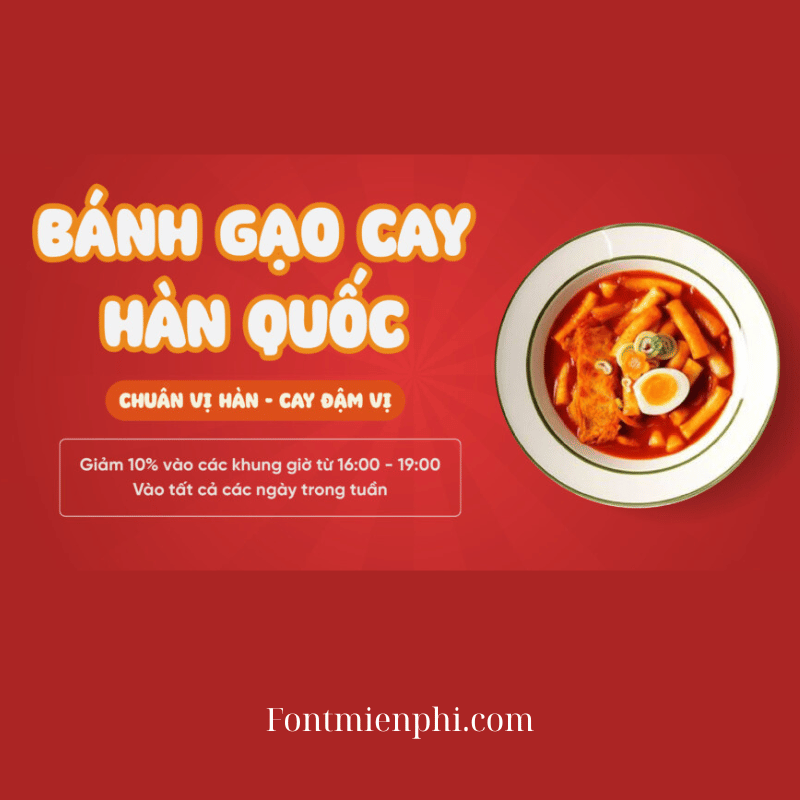
Font Việt Hóa 1FTV VIP Super Foods
Font Việt Hóa 1FTV VIP Super Foods – Phong Cách Độc Đáo Cho Thiết Kế
Giới Thiệu
Font Việt hóa 1FTV VIP Super Foods là bộ font chữ độc quyền, được thiết kế tinh tế dành riêng cho cộng đồng sử dụng tiếng Việt. Với phong cách sáng tạo, nét chữ mềm mại nhưng không kém phần cá tính, font chữ này phù hợp cho nhiều dự án thiết kế, từ ẩm thực, quảng cáo đến thời trang.
Đặc Điểm Nổi Bật
• Thiết kế độc đáo: Nét chữ bo tròn, kết hợp họa tiết sinh động, tạo điểm nhấn cho banner, logo hoặc poster.
• Hỗ trợ tiếng Việt đầy đủ: Bao gồm cả các ký tự có dấu, đảm bảo tính thẩm mỹ và dễ đọc.
• Đa dạng ứng dụng: Phù hợp với thiết kế menu, bao bì sản phẩm, hình ảnh truyền thông liên quan đến ẩm thực, sức khỏe.
Lợi Ích Khi Sử Dụng
Font 1FTV VIP Super Foods giúp sản phẩm thiết kế của bạn trở nên khác biệt, thu hút khách hàng ngay từ cái nhìn đầu tiên. Font chữ này đặc biệt phù hợp với các thương hiệu muốn truyền tải thông điệp tươi mới, năng động.
Kết Luận